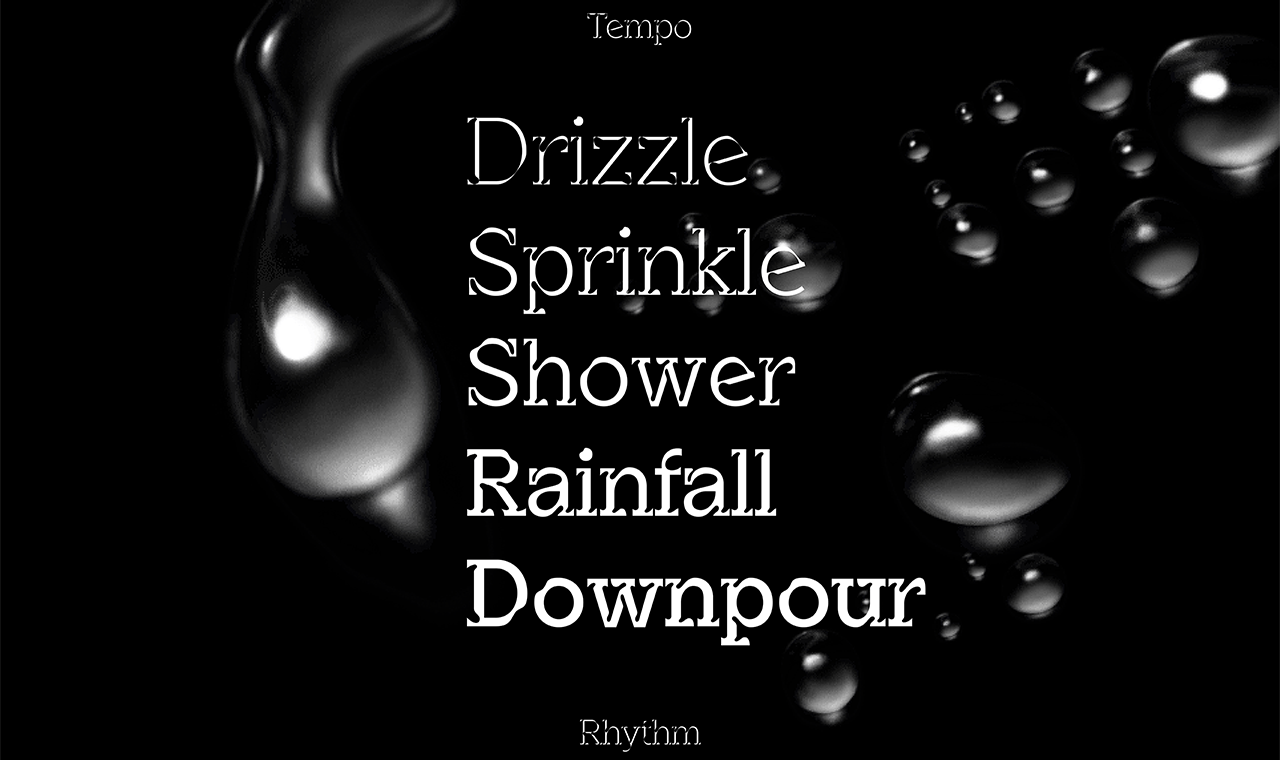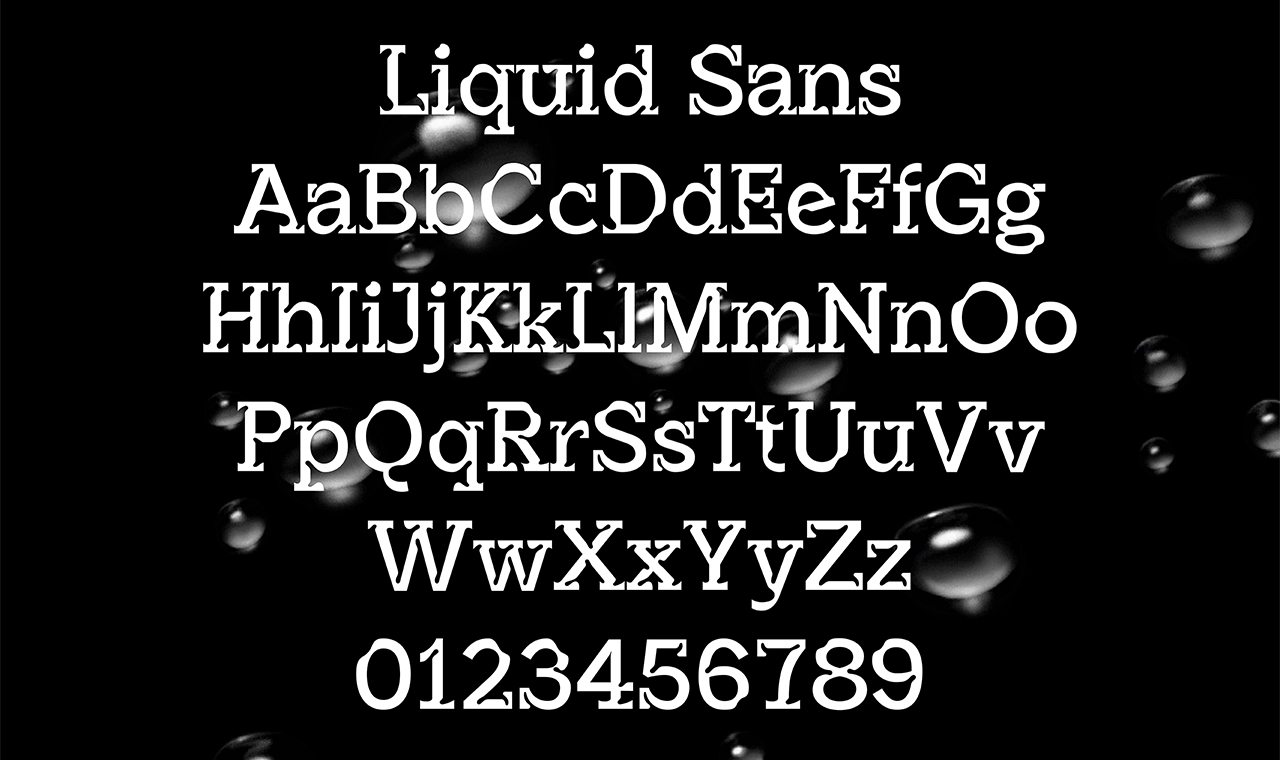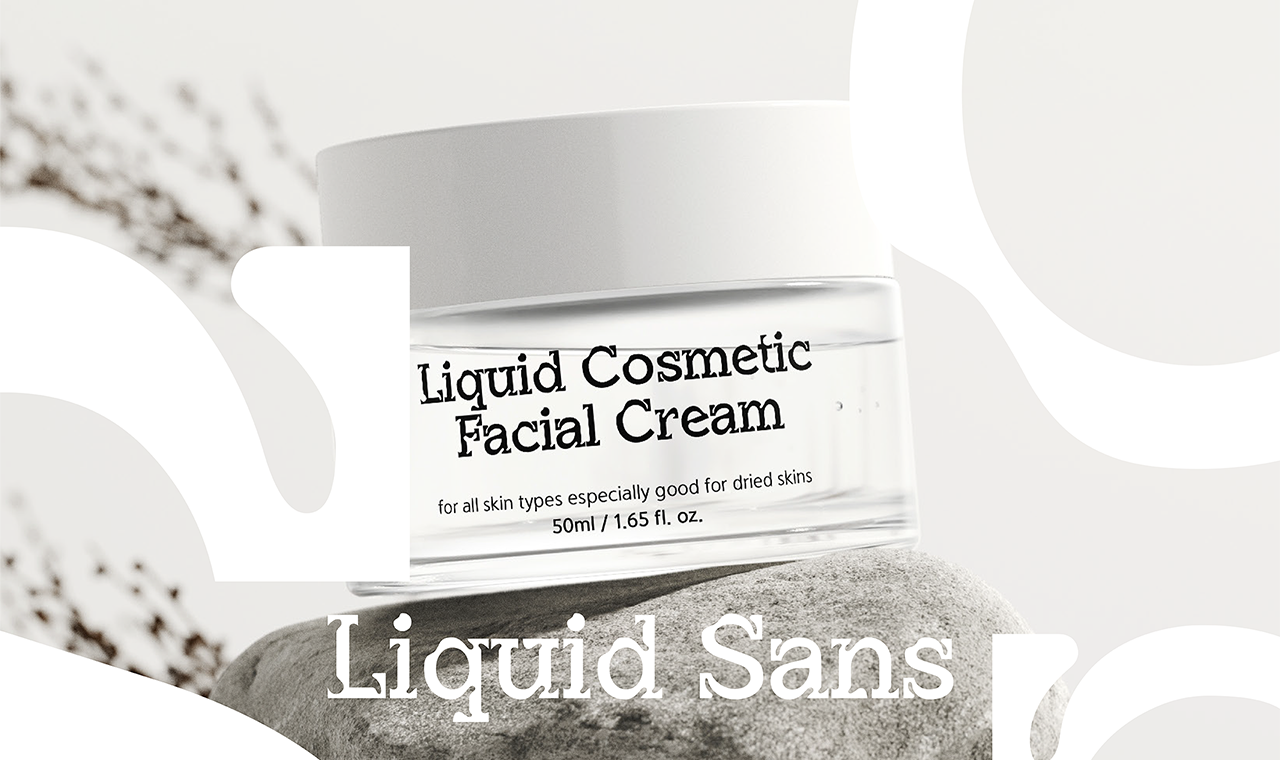
Liquid Sans Variable
Yoon Liquid Sans Variable
윤슬, 물에 빛이 반사되어 반짝이는 잔물결을 뜻합니다. 윤슬의 반짝임과 물의 유기적이고 유연한 모습을 형상화 했습니다.(Yoon Liquid Sans Variable은 Latin 1을 지원하는 라틴폰트입니다.)
장연준, 김지연